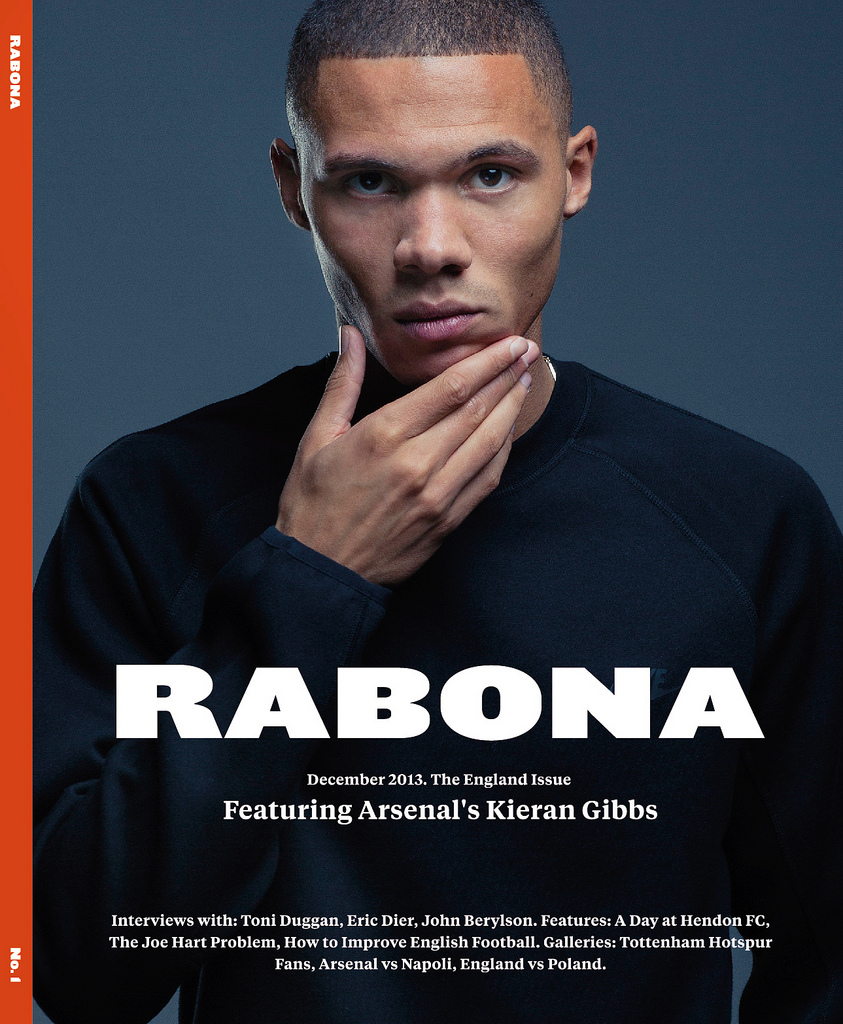
Magazinschriften gesucht (Rabona)
RABONA müsste die Rhode von Font Bureau sein.
leider ist sie das nicht.
Die Maple Black ist noch nah dran und die Bureau Grot Wide Ultra Black. Das O geht wieder eher in Richtung fette Knockout oder Amplitude. Vielleicht wurde das auch zurechtgestutzt.
Nachtrag: Auf der Webseite wird noch die Founders Grotesk Text verwendet.